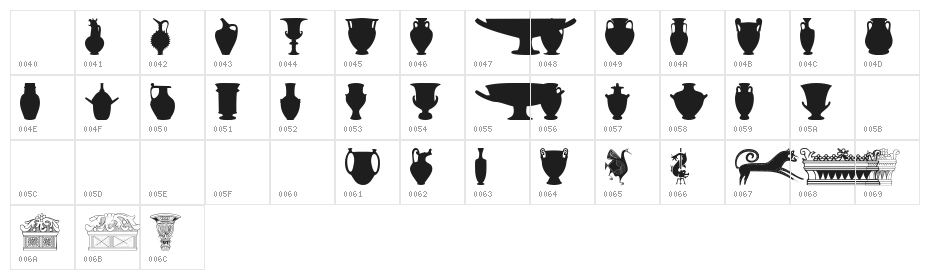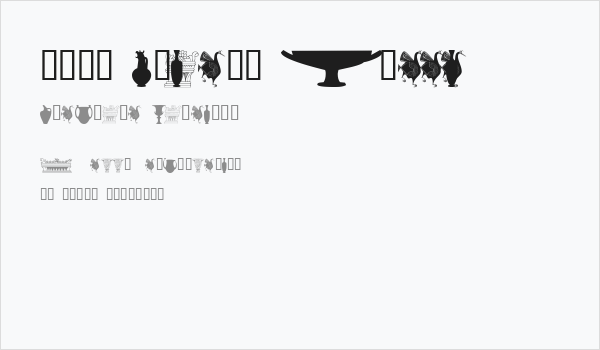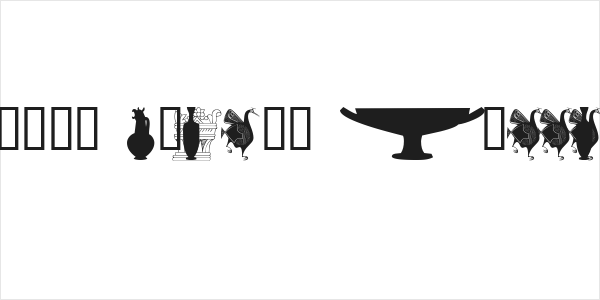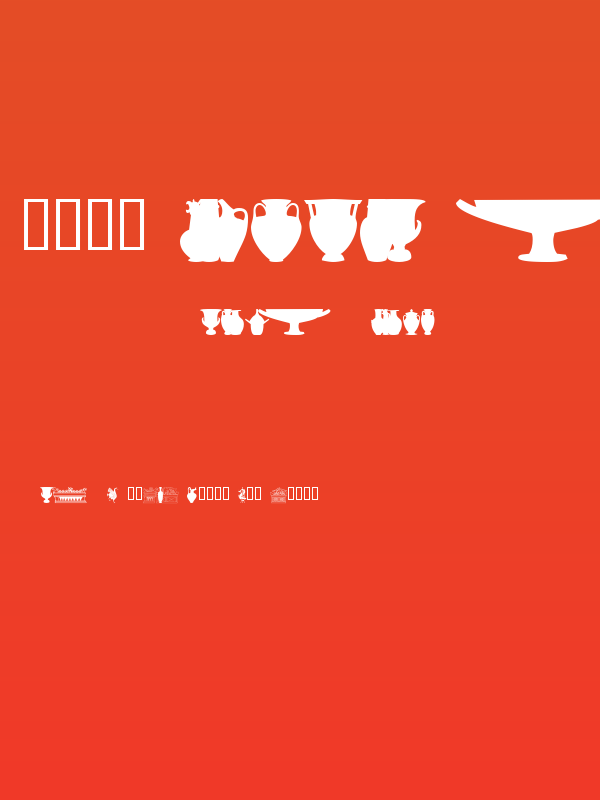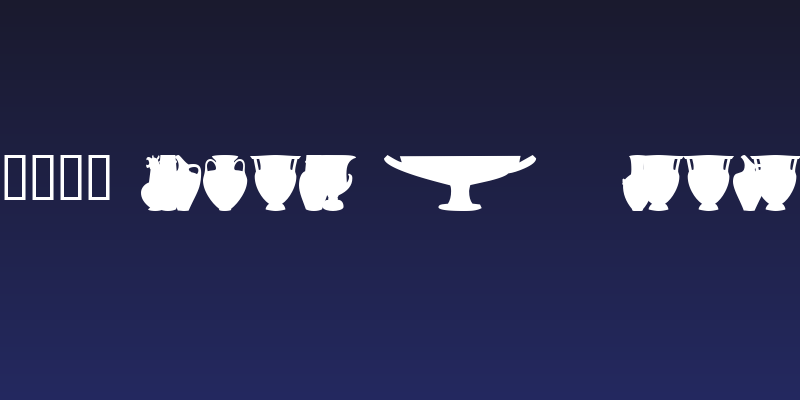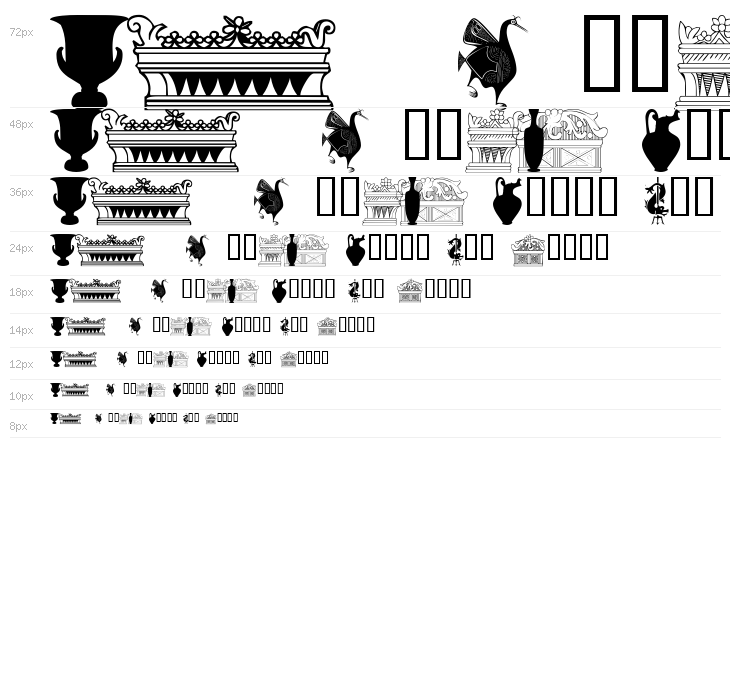
101! Ancient Greece Font
| Gesamtstil | Decorative, Historical |
| Anwendungsfall | Logos, Headlines, Themed graphics |
| Vorgeschlagene Projekte | Museum posters, educational materials, themed event invitations, historical presentations, book covers about ancient Greece. |